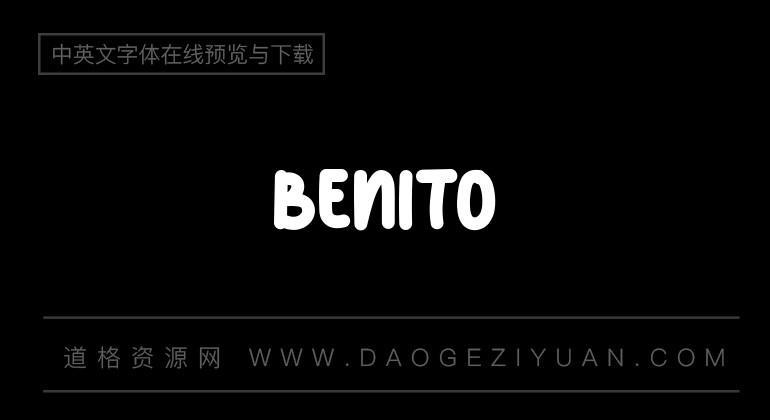
Benito 是一种现代、无衬线的字体,由伊朗设计师 Ceyhun Birinci 创作。其设计风格简单、清晰,字母间的间距适中,使得易读性和美观性都得到了很好的平衡。Benito 字体包括六种不同的字重,从轻到黑,以及西里尔字母和希腊字母等字符的支持。这种字体通常被用于文本排版、海报设计、标志设计等领域。内容介绍
Benito是一款非常不错的手写艺术字体,具有很好的视觉感,适合于文化类的宣传设计、商业类品牌的广告和产品包装设计以及个性化文字排版等较多场景。